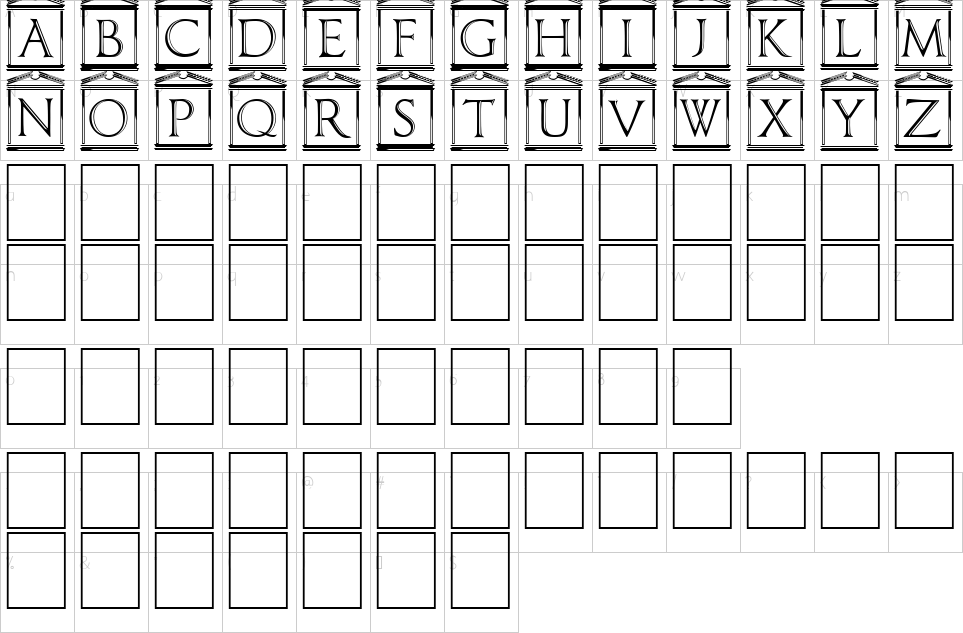
A fonte Paladin Capitals é uma escolha atraente para quem busca uma escrita moderna e alegre, perfeita para aplicações de negócios e designs de interfaces de usuário. Desenvolvida pelo designer Paul Lloyd, essa fonte pode ser facilmente usada tanto em sistemas Windows quanto Mac, o que a torna uma escolha versátil para diferentes plataformas. Com sua simplicidade e elegância, Paladin Capitals adiciona um toque moderno a qualquer design, seja ele para logotipos, títulos de slides ou gráficos de negócios. Desde que foi lançada, a fonte Paladin Capitals tem sido descarregada mais de 5.685 vezes, e é a escolha ideal para quem deseja incorporar um estilo distintivo em seus projetos de design.